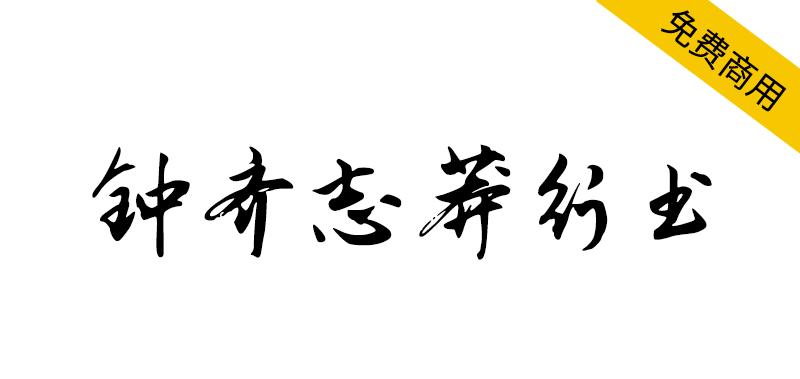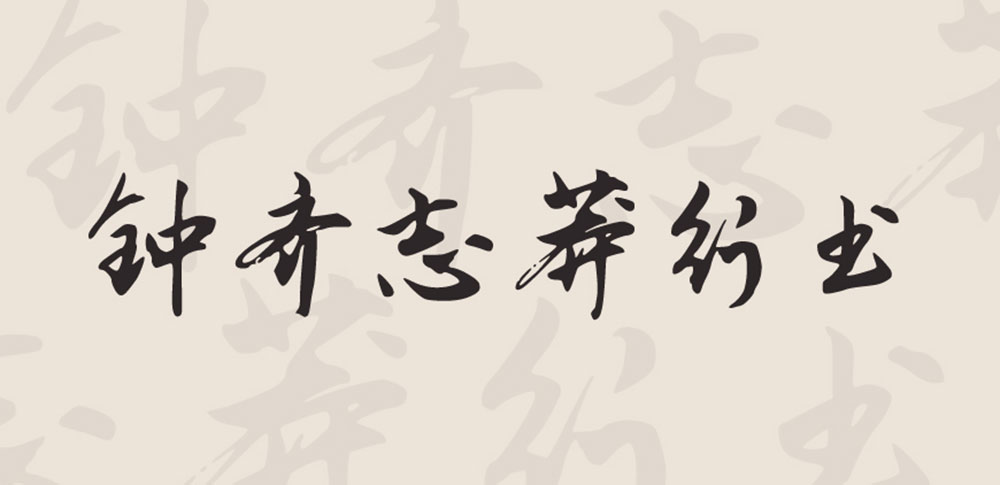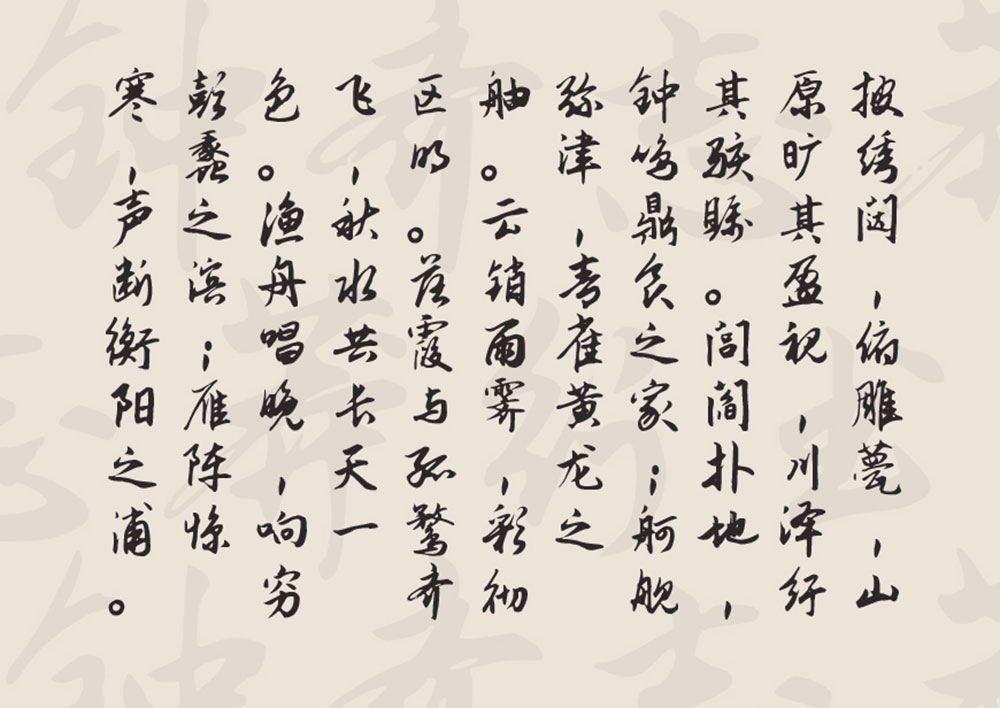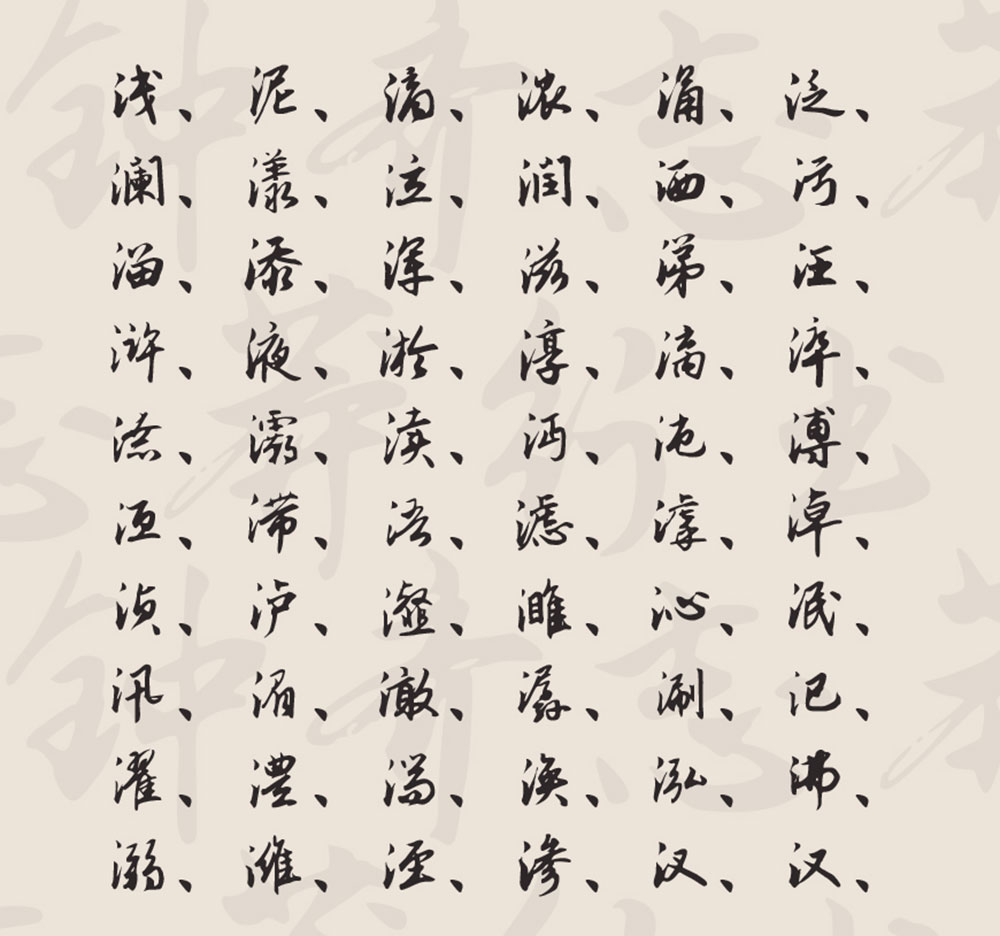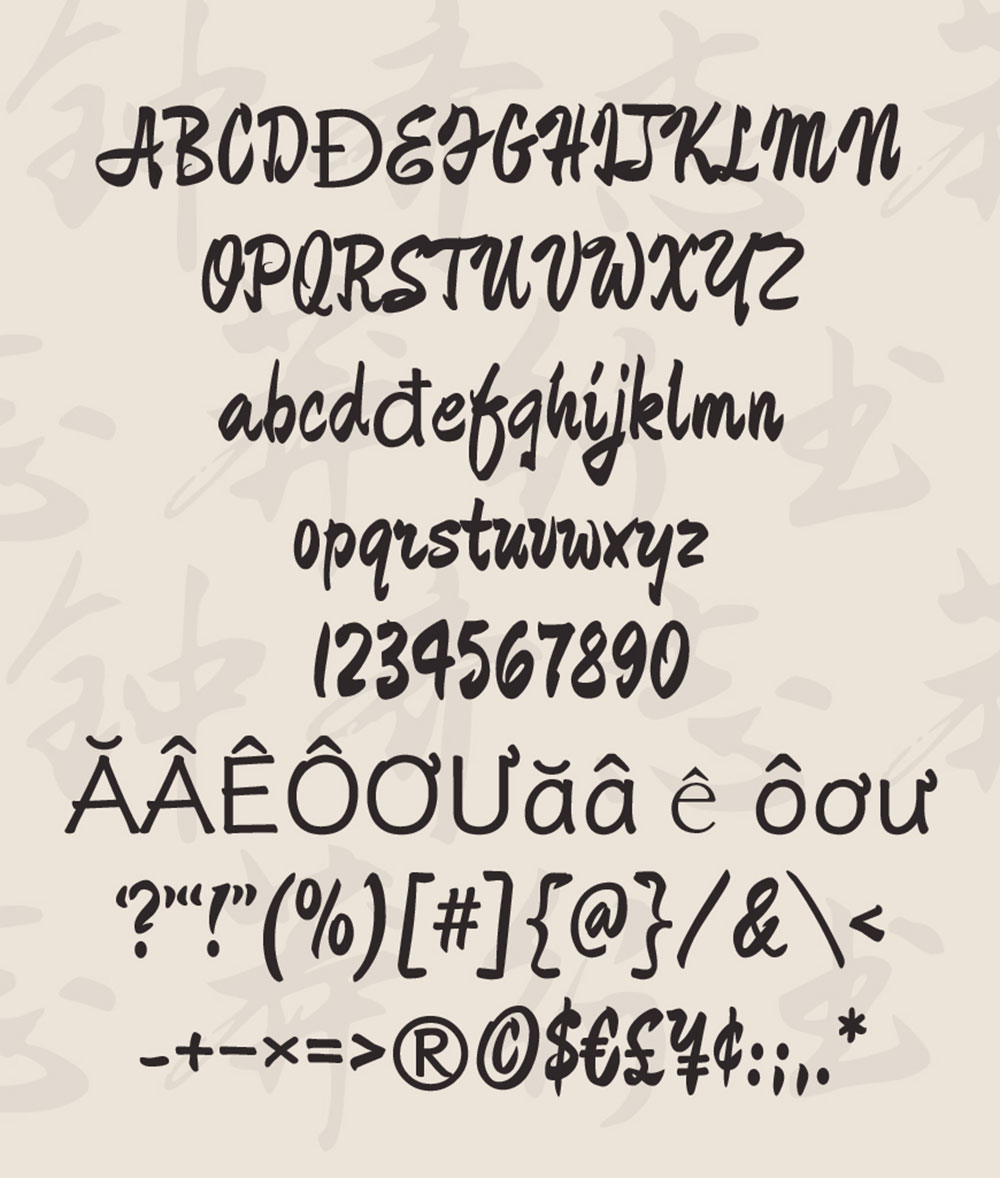
钟齐志莽行书是谷歌开源字体项目里的一款中文行书书法字体,遵循SIL Open Font License 1.1授权许可,由作者书法家韦志莽先生授权钟齐字库把这款字体上传至Google fonts开源字体项目,钟齐志莽行书这款字体字形潇洒飘逸,形体端秀而骨架劲挺,整体效果非常出色,可广泛用于广告设计、包装设计等方面。